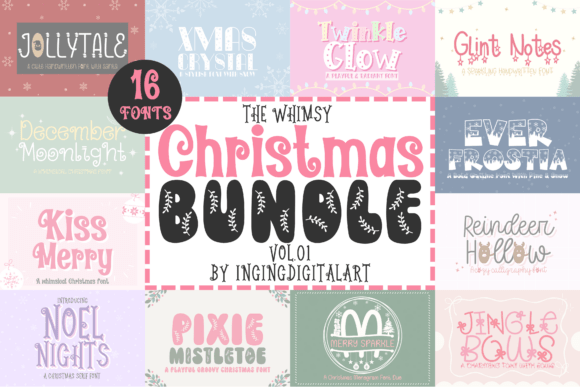
The Whimsy Christmas Bundle Vol.01
หากคุณกำลังมองหาเนื้อหาคุณภาพสูงเช่น The Whimsy Christmas Bundle Vol.01 แพ็คเกจพรีเมียมนี้เป็นตัวเลือกที่ยอดเยี่ยมสำหรับโปรเจ็กต์สร้างสรรค์ของคุณ
สร้างขึ้นอย่างแม่นยำ The Whimsy Christmas Bundle Vol.01 ให้เวกเตอร์ที่สะอาด พิมพ์ตัวอักษรที่ราบรื่น และใบอนุญาตเชิงพาณิชย์เพื่อความสบายใจ
ไม่ว่าคุณจะสร้างผลิตภัณฑ์ POD (Print on Demand) คำเชิญงานแต่งงาน หรือกราฟิกโซเชียลมีเดีย The Whimsy Christmas Bundle Vol.01 ก็เหมาะสมอย่างยิ่ง